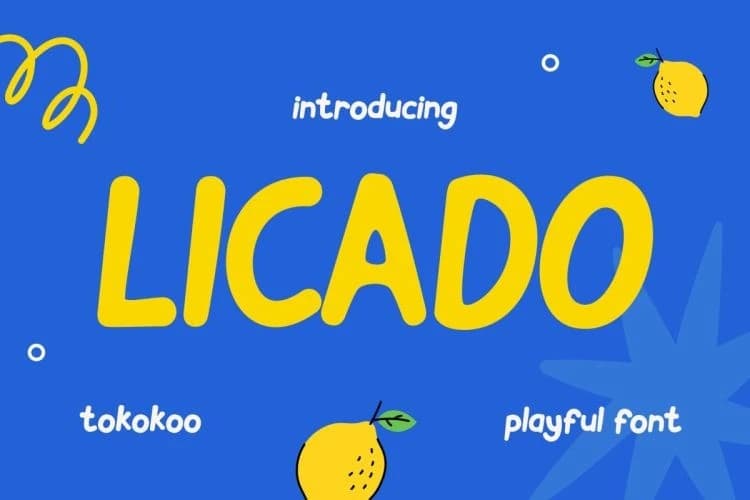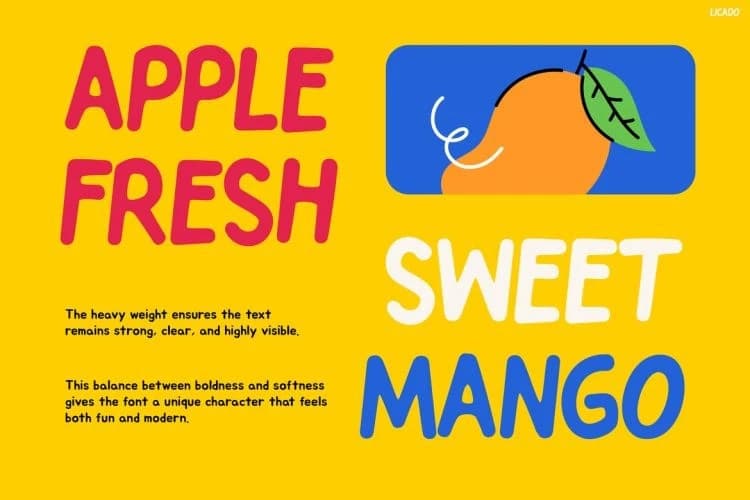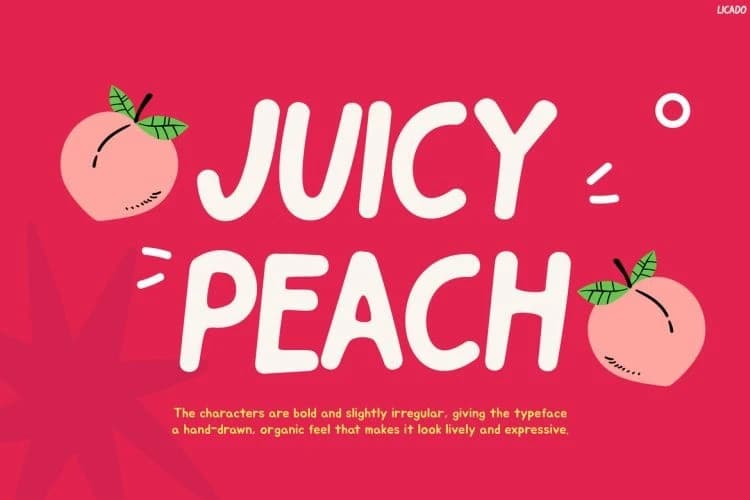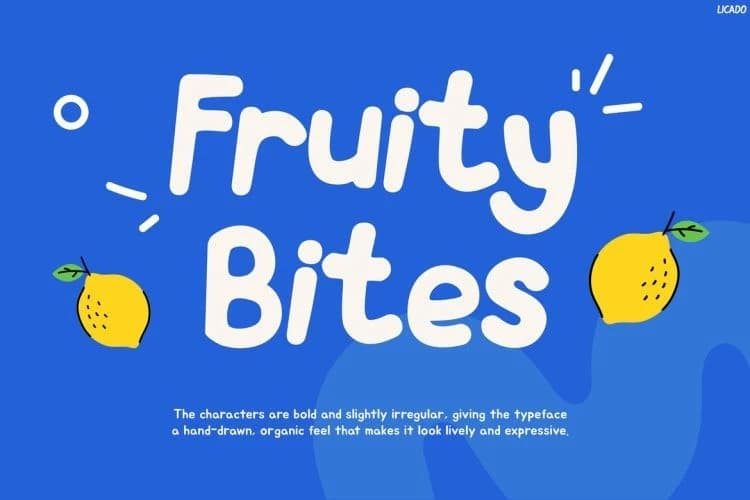
Licado Playful Font
Licado Playful Font, yaratıcı çocuk temalı tasarımlara eğlence, renk ve kişilik katması için tasarlanmış parlak ve neşeli bir gösterişli yazı tipidir. Yuvarlak hatlı harf biçimleri, oyuncu eğriler ve davetkâr oranlar, anında canlı ve sıcak bir görünüm yaratır.
Licado Playful Font, çocuk temalı yaratıcı tasarımlara eğlence, renk ve kişilik katması için tasarlanmış parlak ve neşeli bir gösterim yazı tipidir. Yuvarlak harf biçimleri, neşeli eğrileri ve dostane oranları ise anında canlı ve davetkar bir görünüm yaratır.